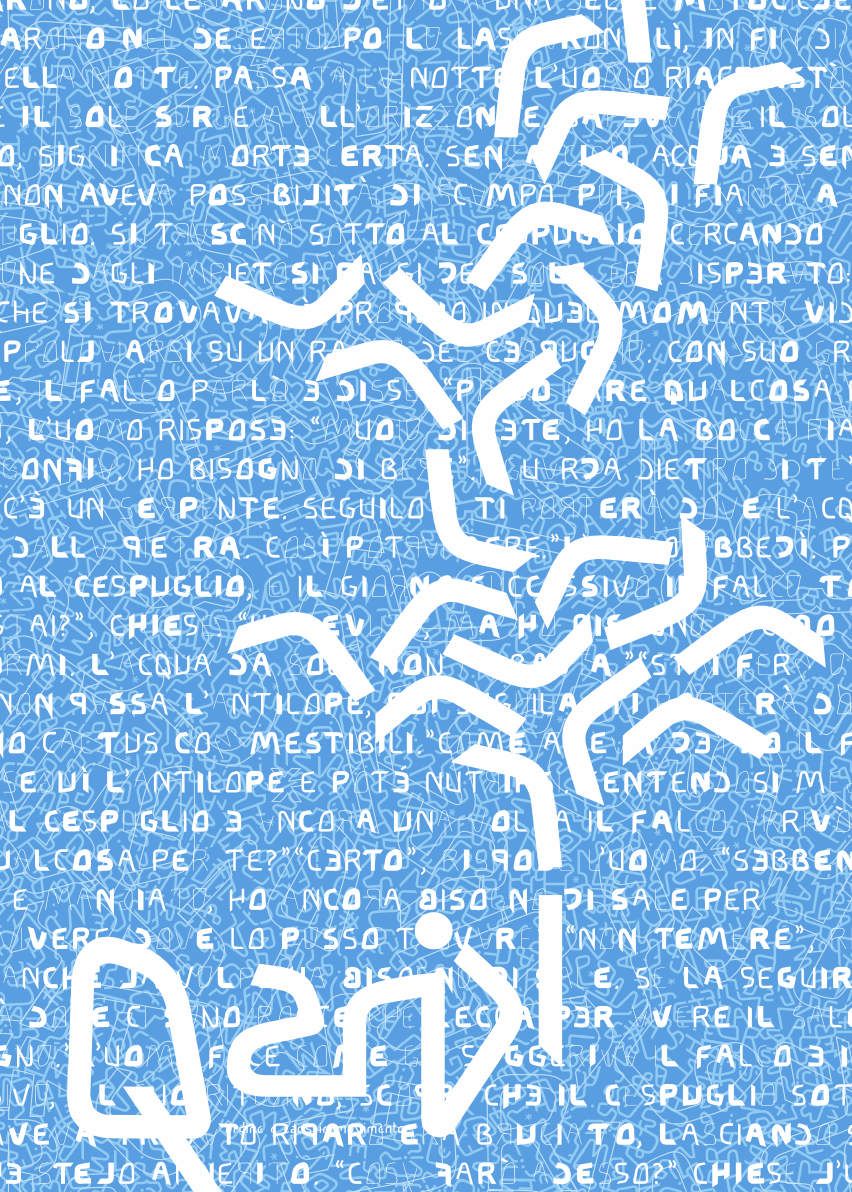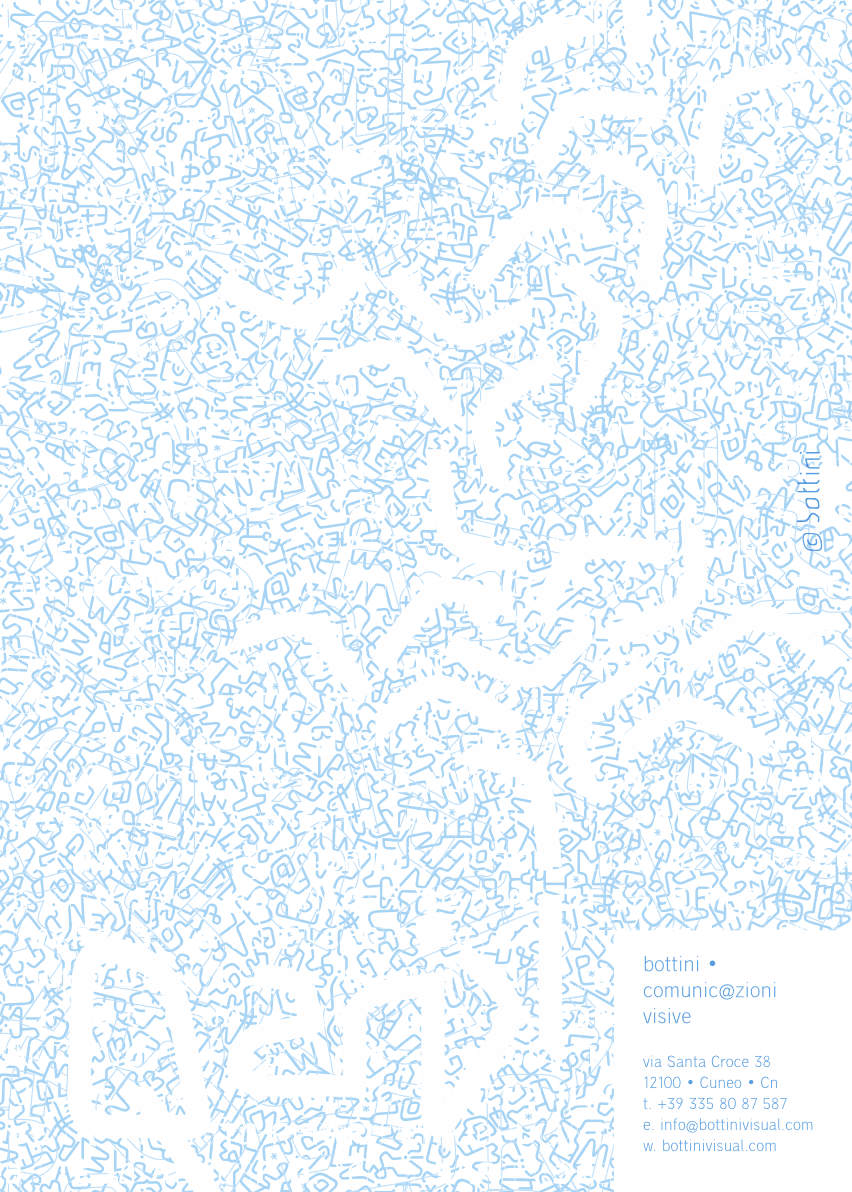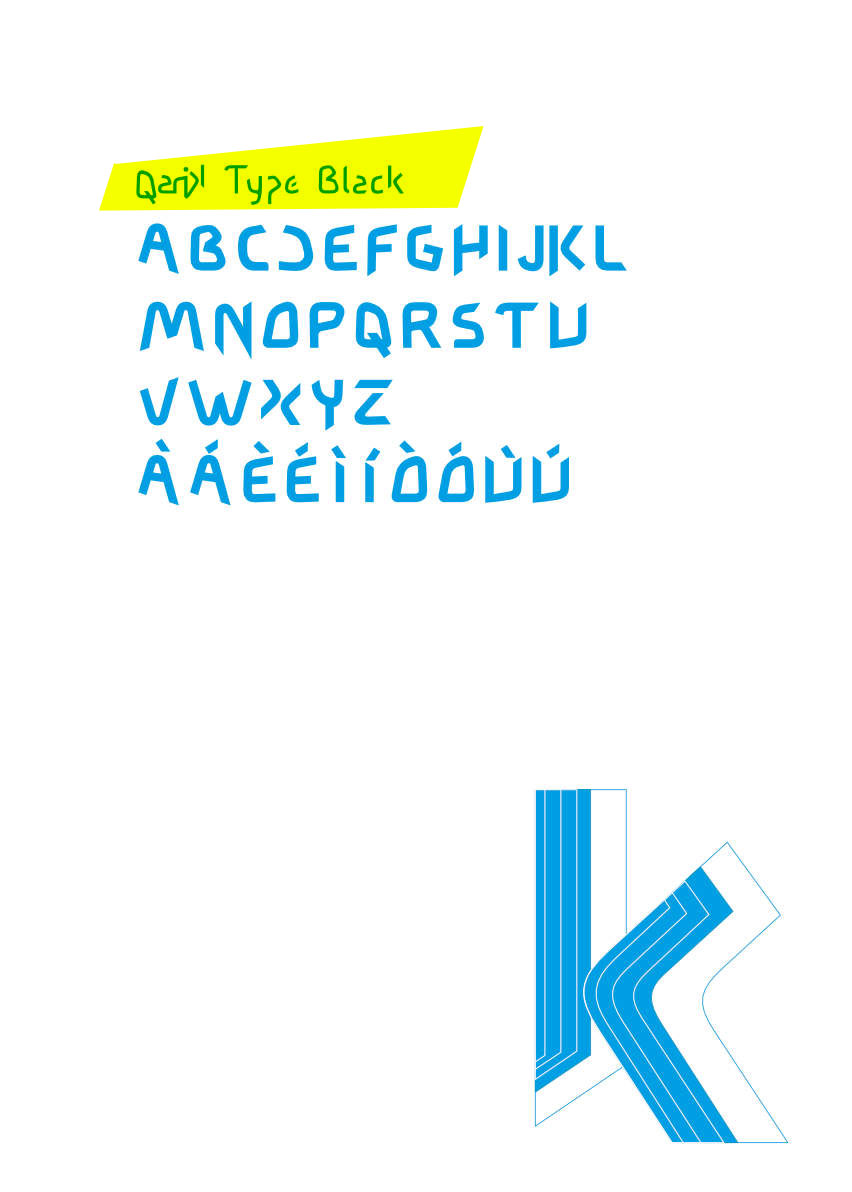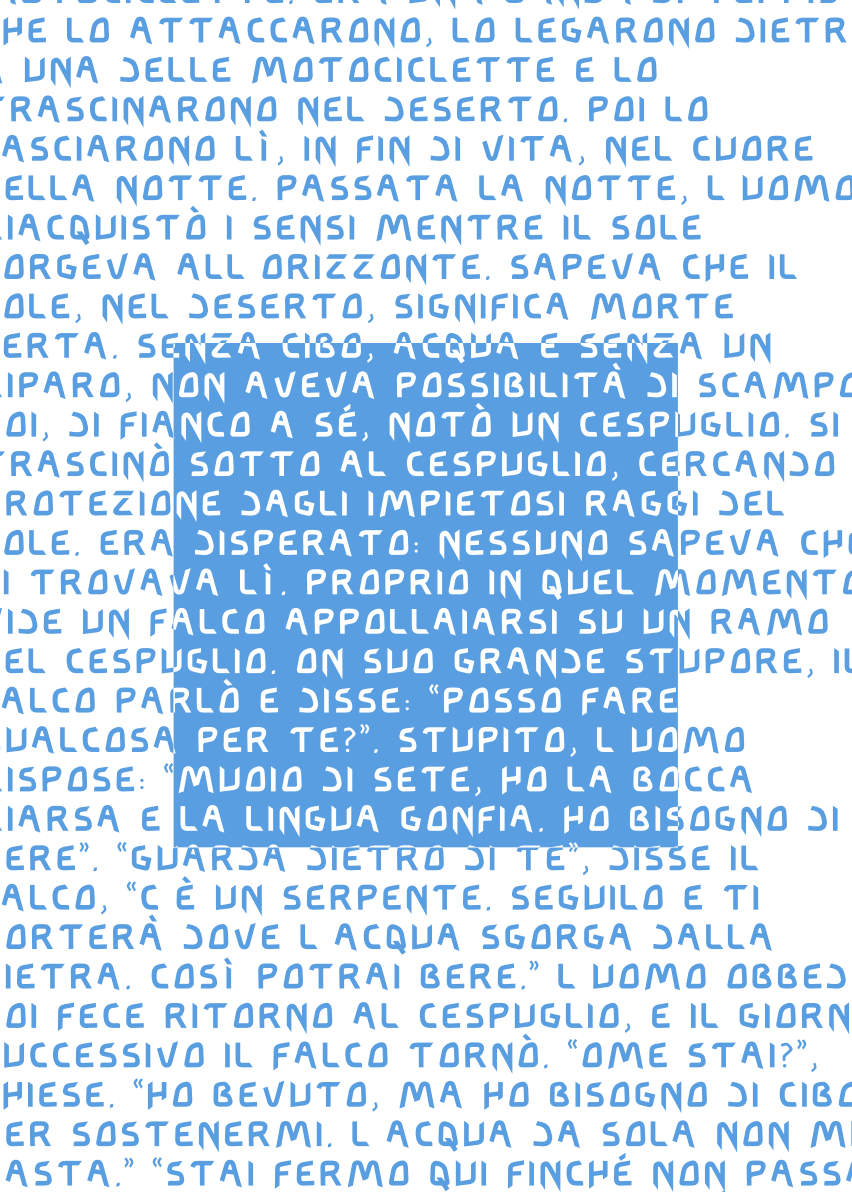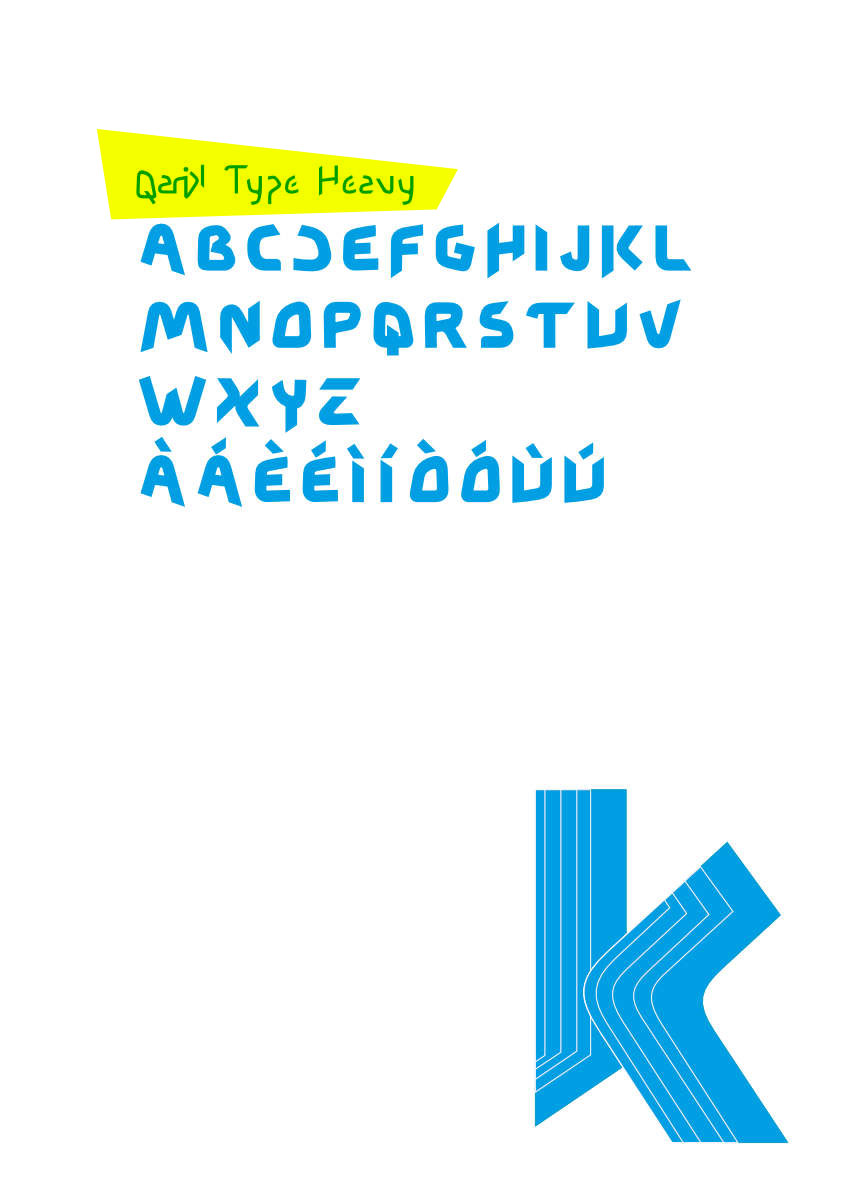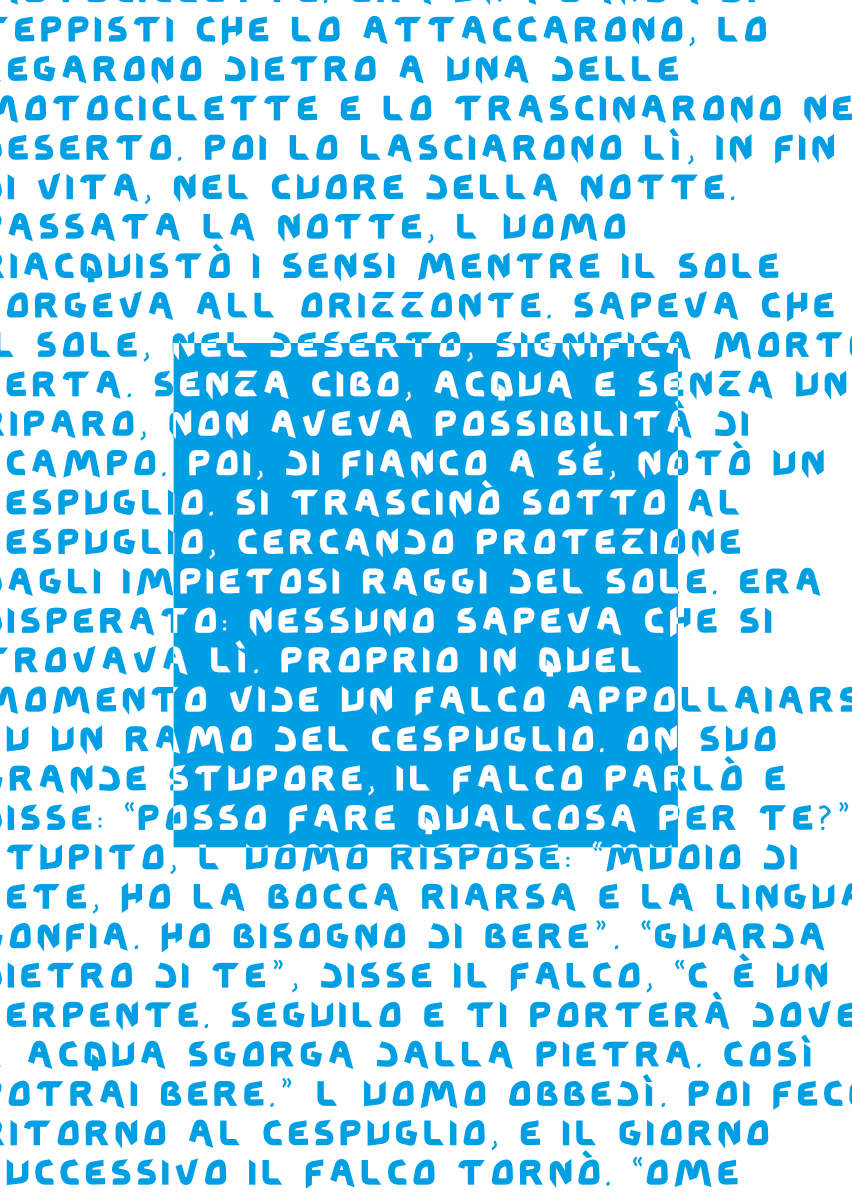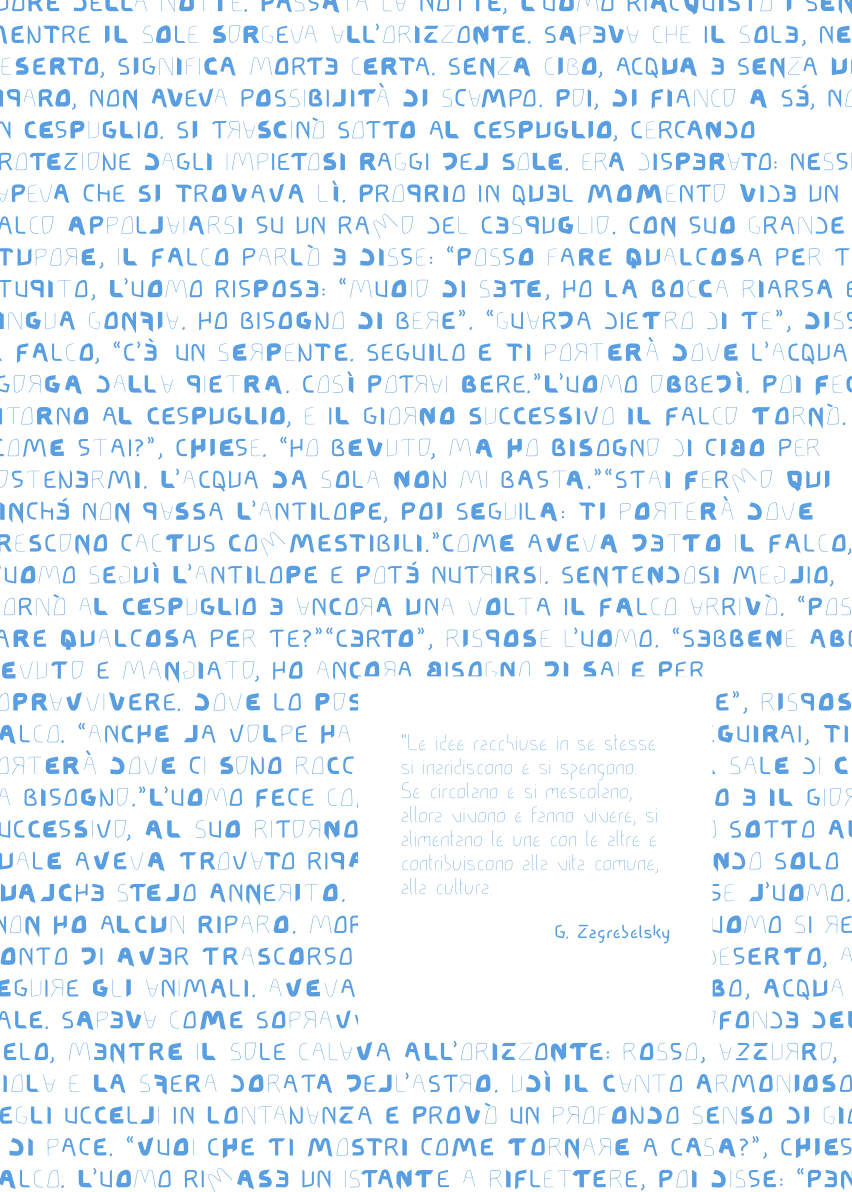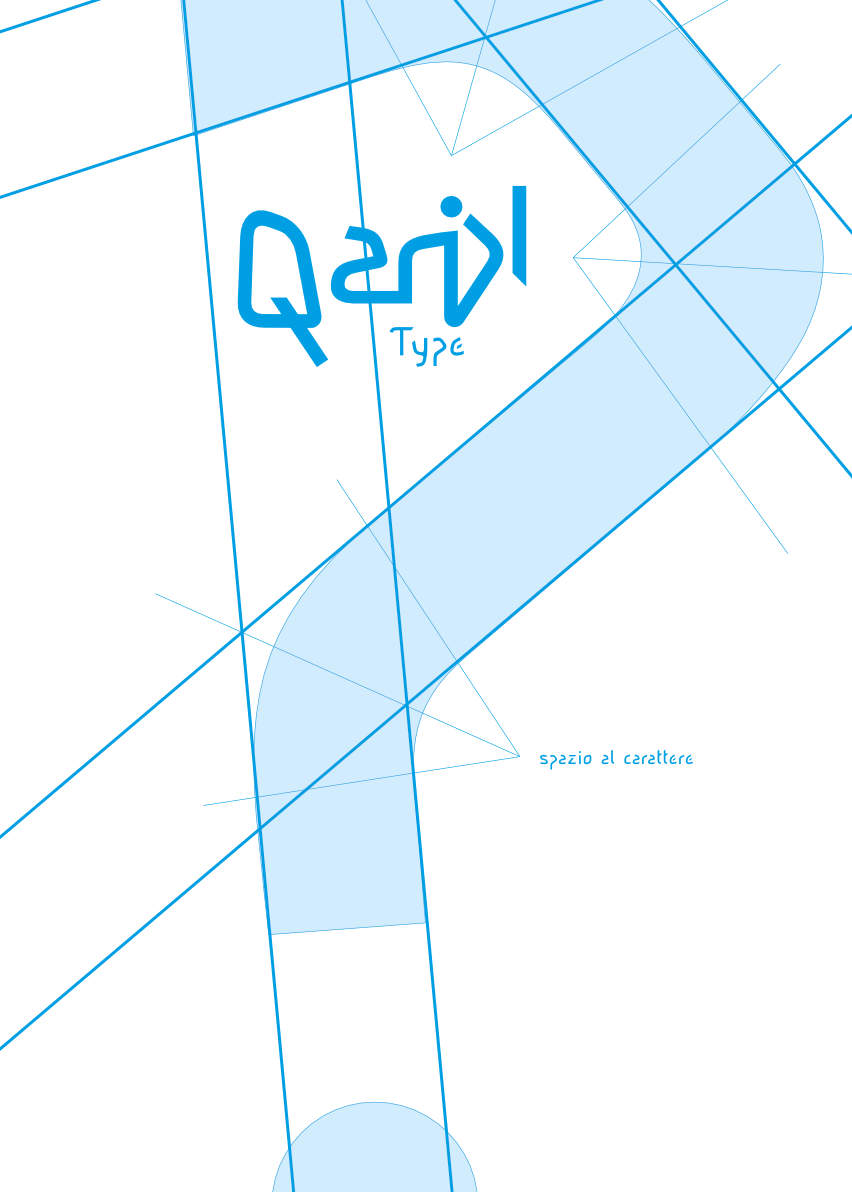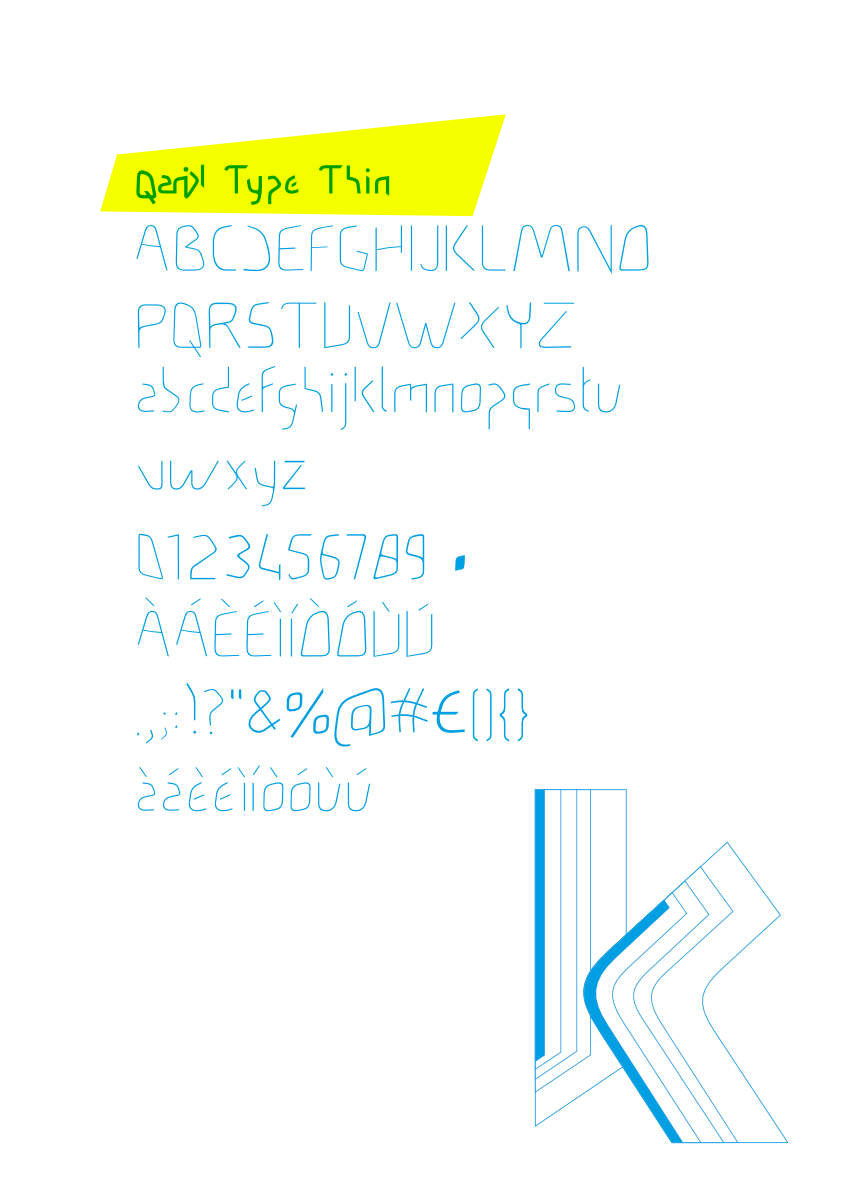
QanikType nasce come identità per Qanik, uno spazio aperto, multidimensionale e multidisciplinare, dove mestieri, tecnologie e idee si incontrano e si scontrano tra ordine e caos sul terreno dell’espressione visiva!
Ho disegnato questa font per rappresentare queste due forze contrapposte, quale sia l’una o l’altra, lascio all’osservatore e alla curiosità delle sue emozioni il compito di scoprirlo.
Trae ispirazione da forme arcaiche e artigiane della scrittura ma si plasma su di una modernità e dinamicità tipiche della tecnologia contemporanea.
La ricerca si è focalizzata su forme semplici, su segni che ricordino la scrittura incisa, ma che siano strutturalmente opposte ad essa.
I glifi vorrebbero ricalcare un fare di getto, in alcuni casi ricordano la stenografica, ma hanno radici lontane: i graffiti preistorici e le antiche incisioni rupestri. La loro essenzialità, estremizzata in taluni segni, è volta ad eliminare l’eliminabile sino al limite della leggibilità e riconoscibilità dell’alfabeto. Le geometrie volutamente si allontanano dalle forme classiche, e l’assenza delle grazie è quasi totale, di loro rimane solo un ricordo nei tagli inclinati che chiudono alcune aste.
Dalla modernità attinge forme quasi sempre raccordate e la quasi totale assenza di parallelismi. Il cuore tecnologico è dove maggiormente viene esaltata l’intrinseca contraddizione di questo carattere, con questo font, è possibile comporre testi mutevoli, di volta in volta differenti di ritmo e peso, e che si alternano in chiaroscuri a volte delicati e altri stridenti, mantenendo però stabile una regolarità quasi sottovoce. A prima lettura sembra un codice indecifrabile, una scrittura Fenicia, ma ben guardando il codice svanisce per lasciar posto a forme che via via si fan sempre più chiare e riconoscibili…